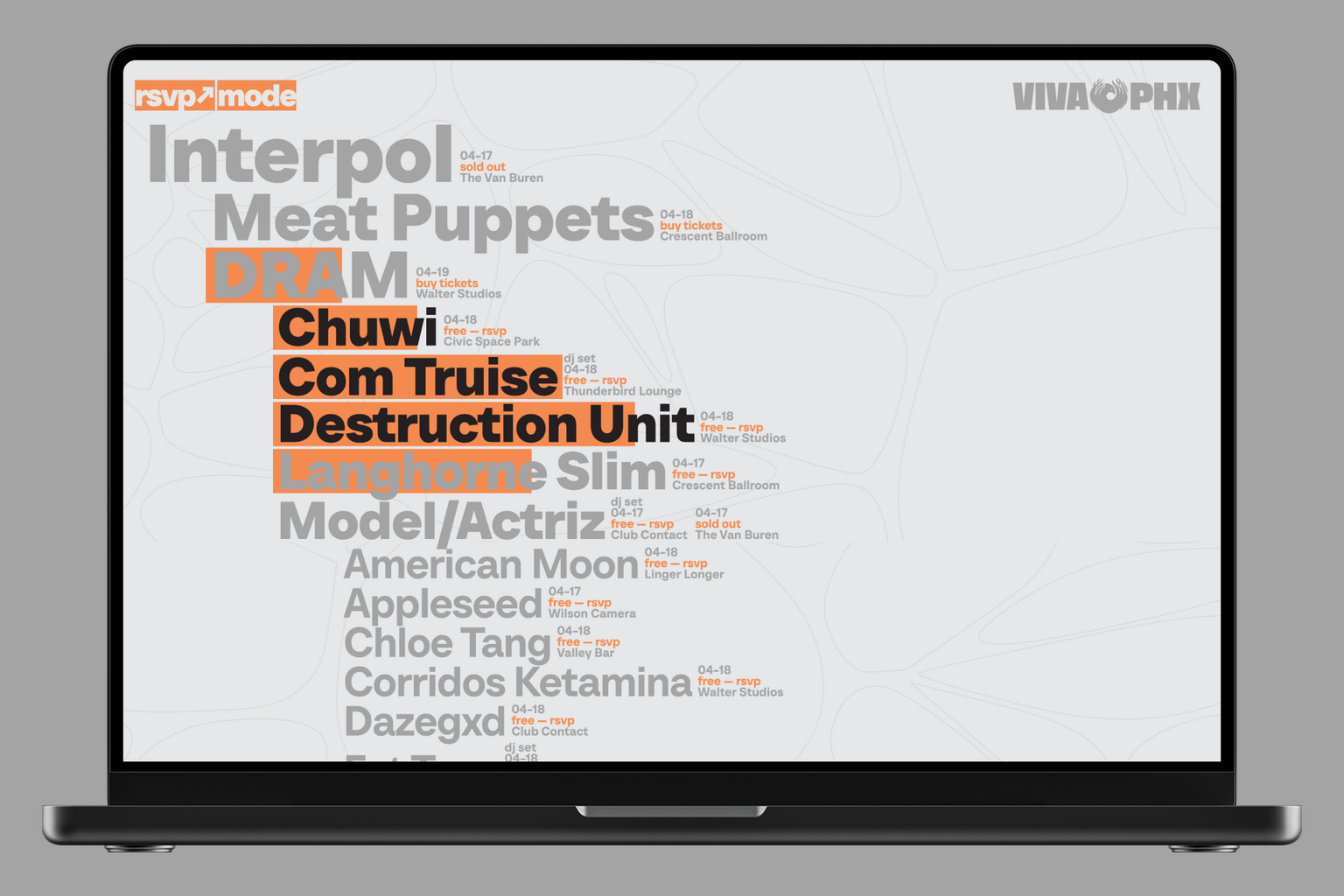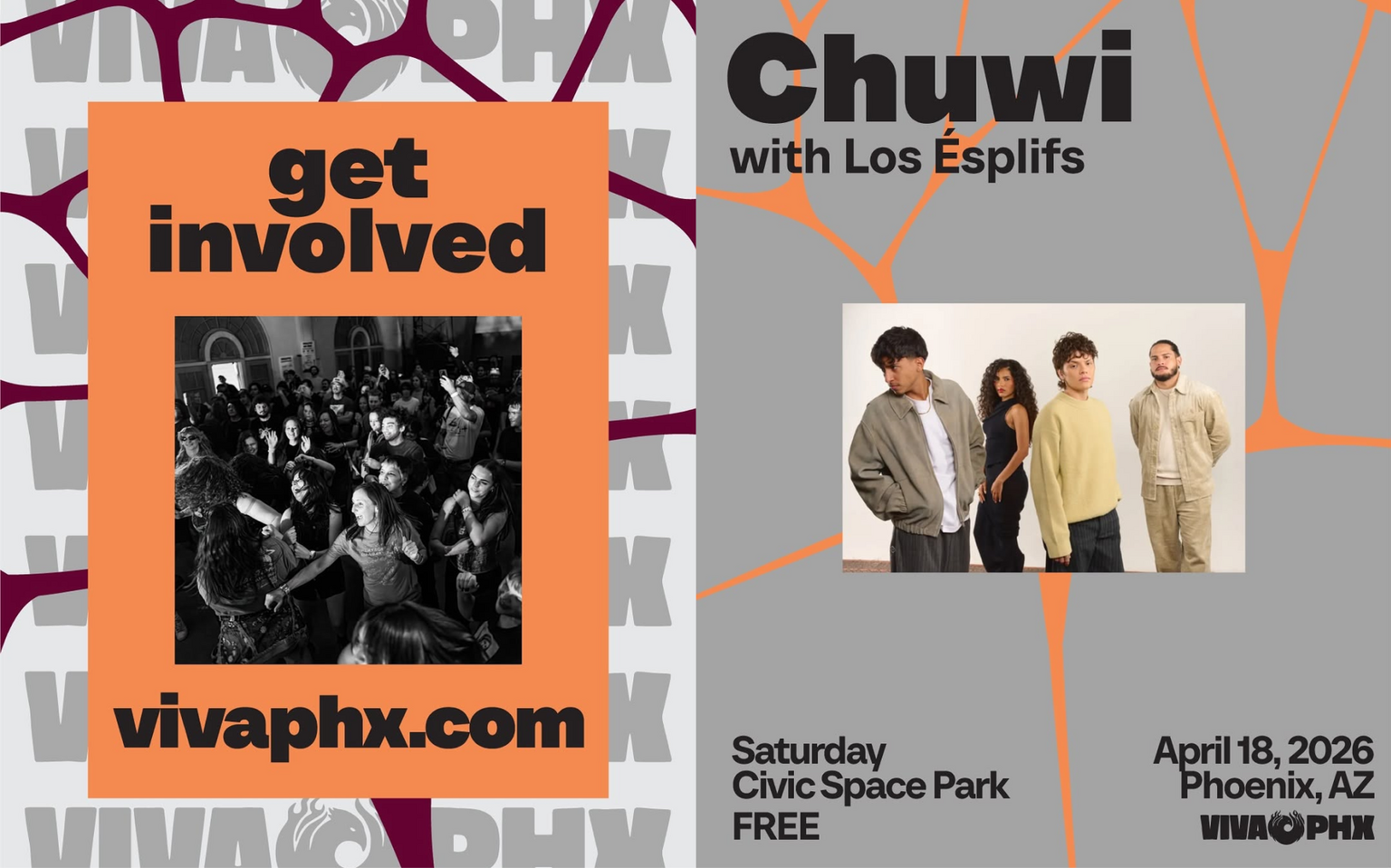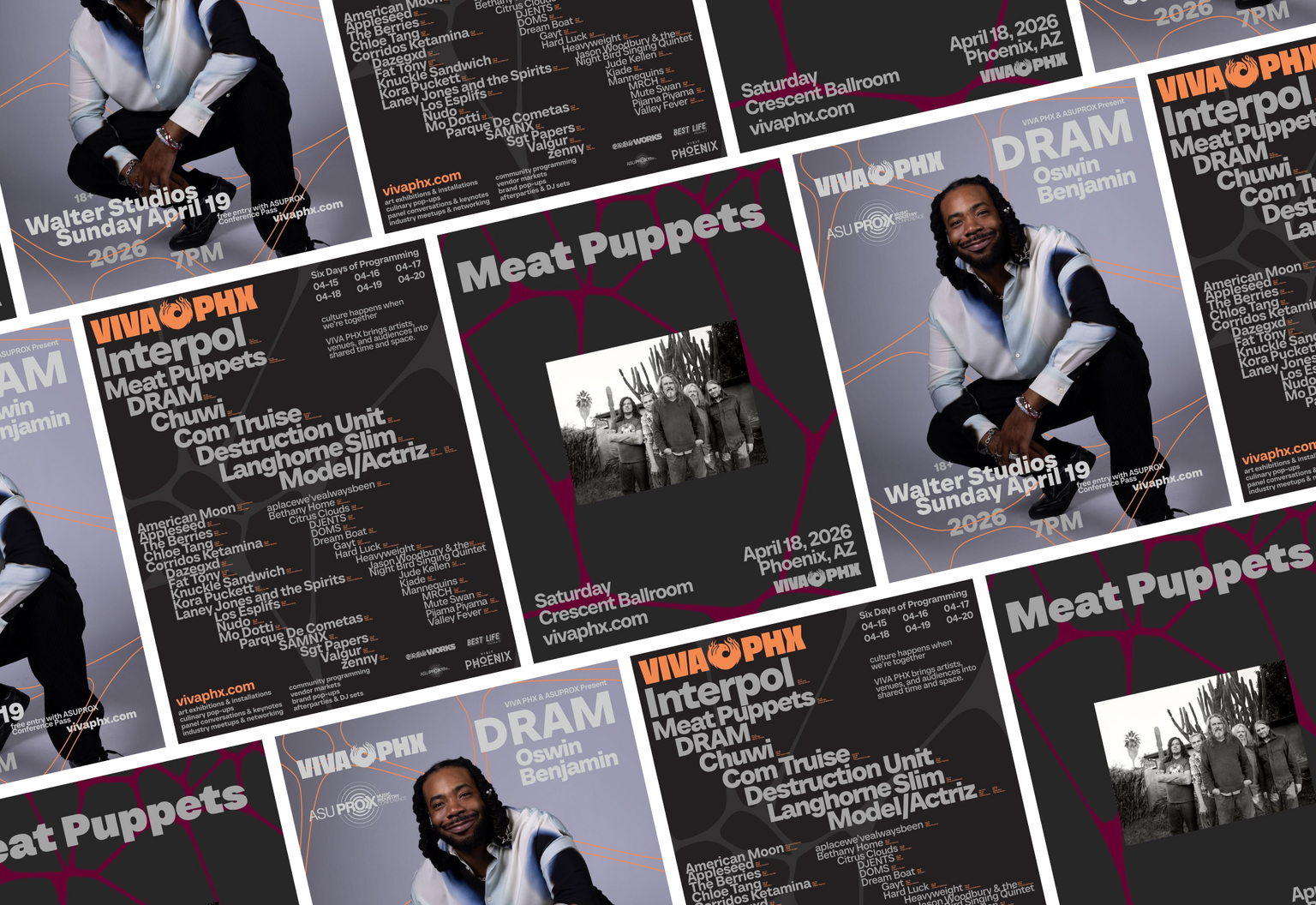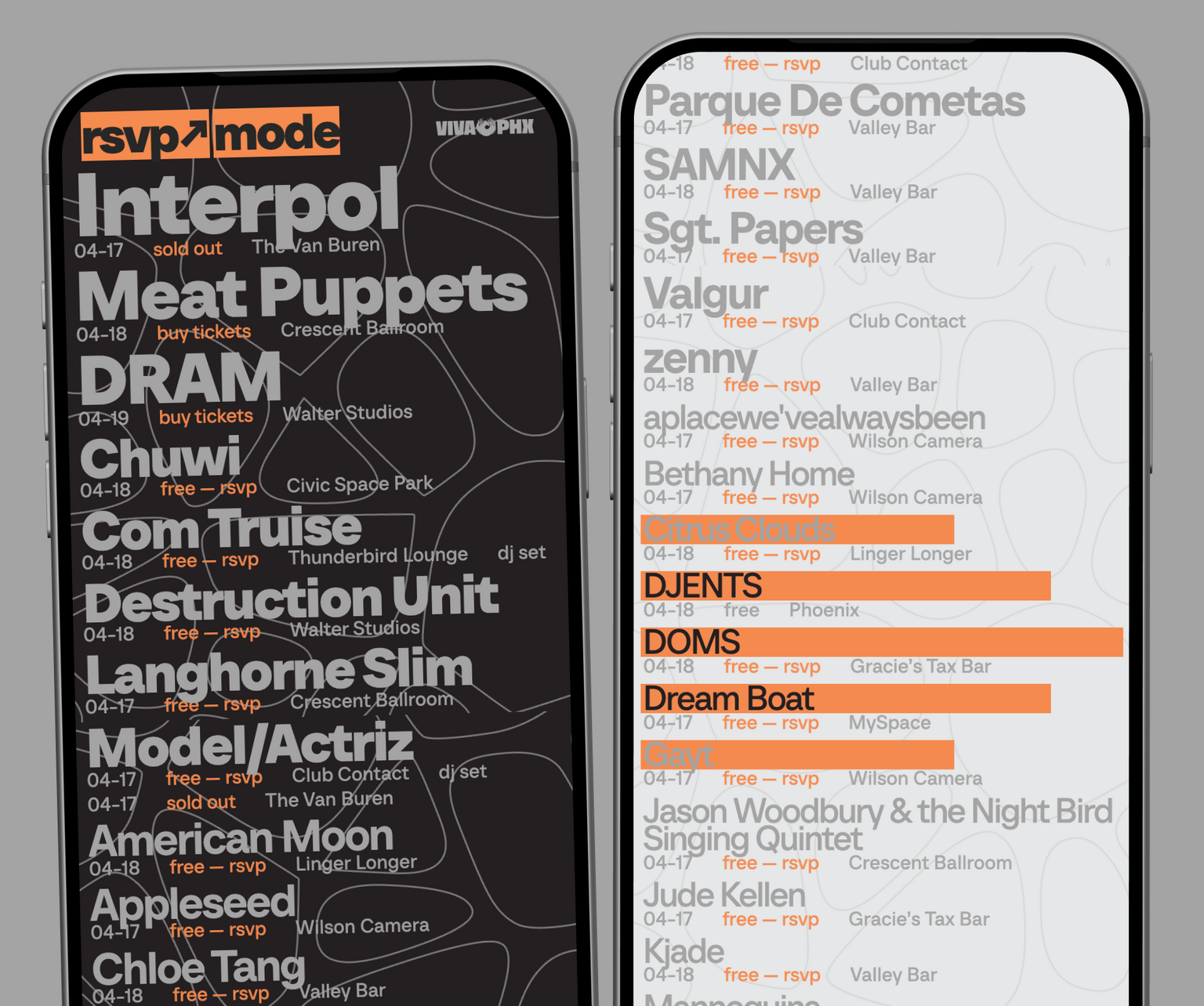
ТТ Неорис (TT Neoris) используется в айдентике американского фестиваля VIVA PHX.
VIVA PHX — это ежегодное мероприятие, во время которого город Финикс превращается в одну большую площадку для музыки, еды, искусства и живого общения. Наш шрифт помогает чётко выстроить иерархию на сайте, чтобы посетители могли быстро ориентироваться в программе, а также подчёркивает современный лаконичный дизайн.